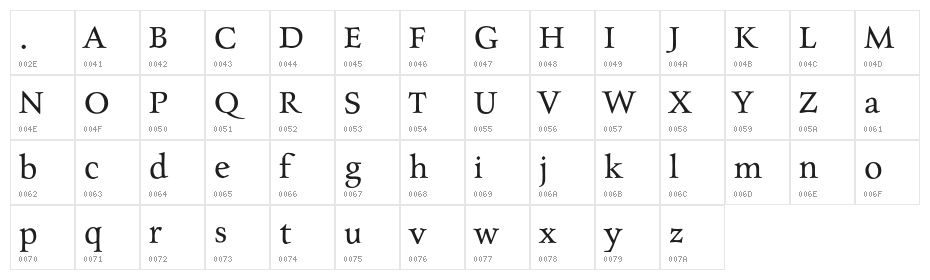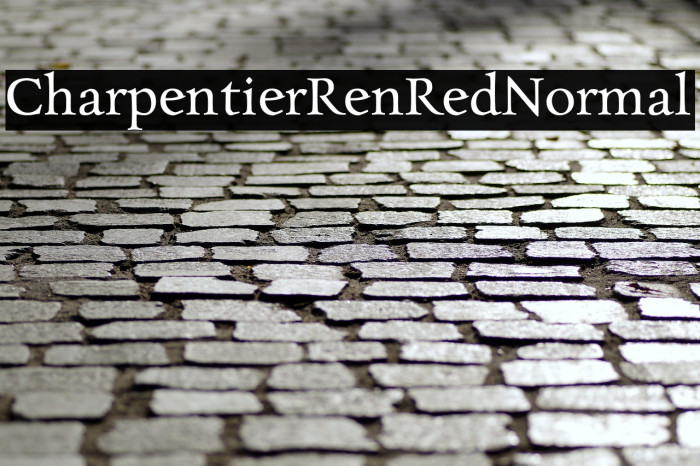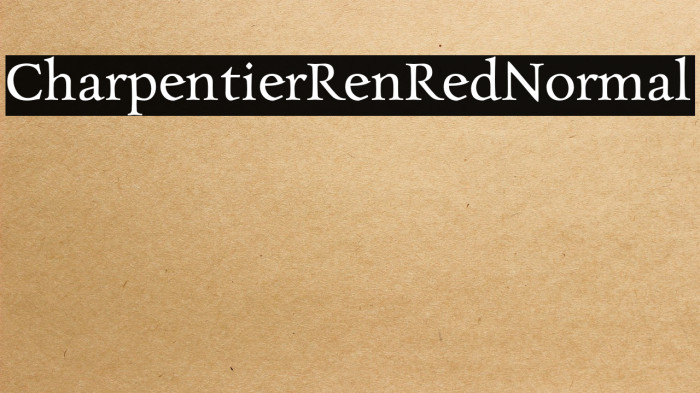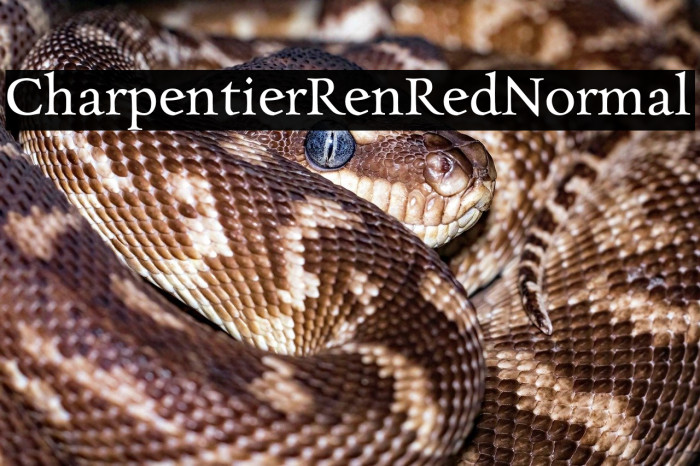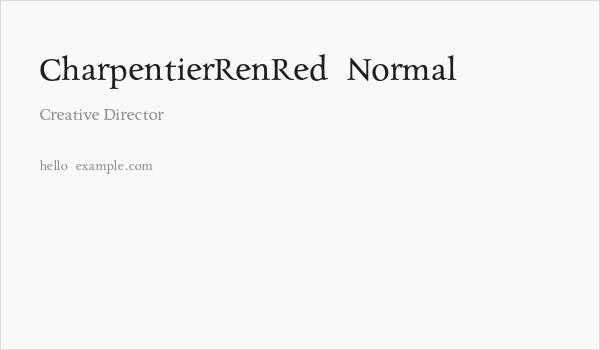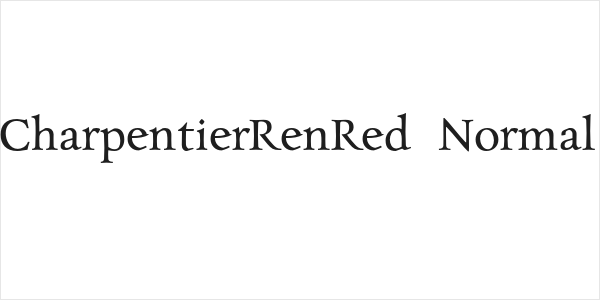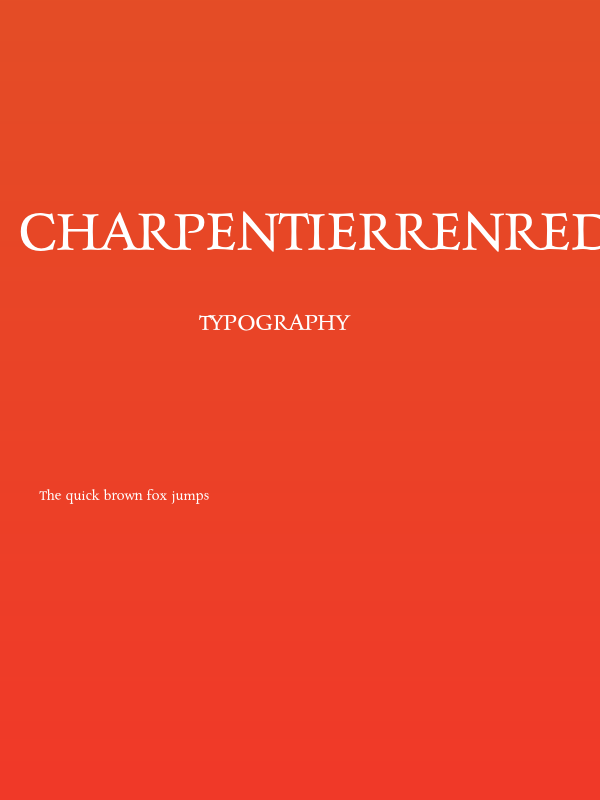
CharpentierRenRed-Normal Font
| 整体风格 | Classic |
| 使用场景 | Headlines, Body text, Logos |
| 推荐项目 | Ideal for book covers, formal invitations, historical documents, and branding that requires a classic touch. |